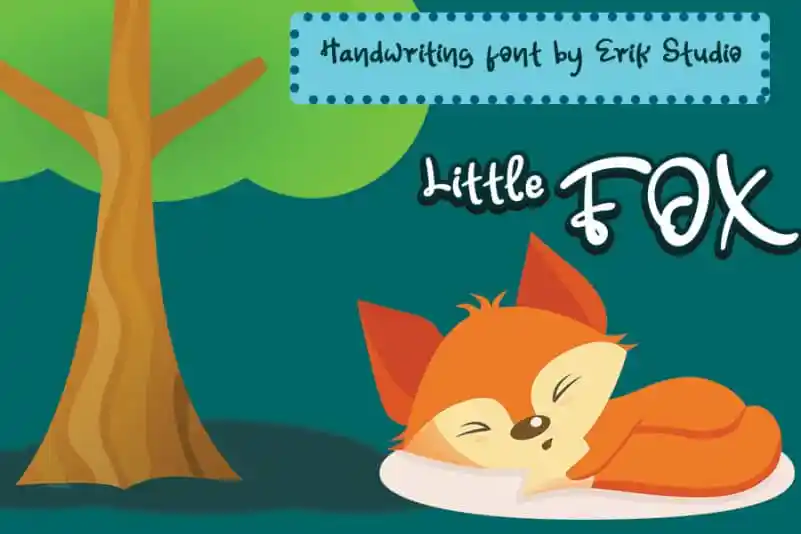
Littel Fox Display Font – Download Grátis
Littel Fox Display Font é uma delicada tipografia de alfarroba com traços que dançam ao longo da linha base. Alegre e romântica, essa fonte será perfeita para escrever cartas de casamento, anúncios ou qualquer outro design que precise de um toque personalizado e romanticamente agradável. Esse estilo delicado e encantador certamente enriquecerá suas criações gráficas com um toque único e especial. Para quem busca uma fonte para escritas especiais, Littel Fox Display Font é uma escolha impecável que traz ao seu design um toque de romantismo refinado.